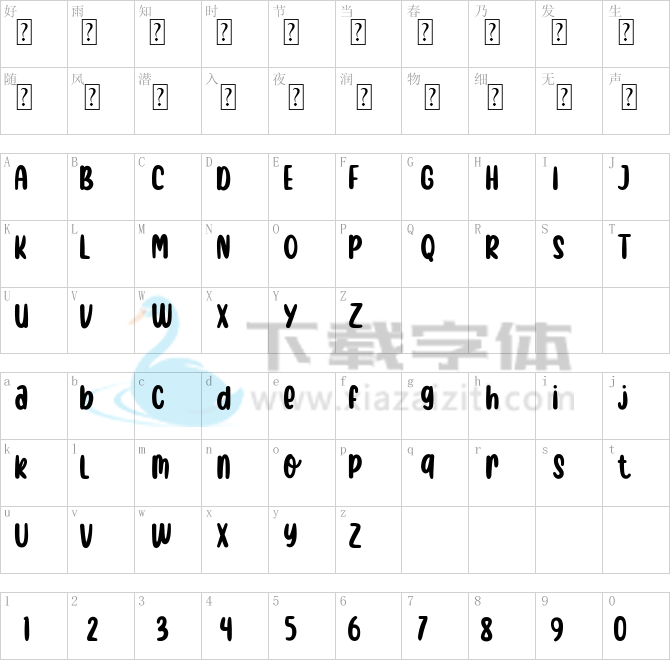
Alexander Display.ttf字体下载,这款字体结构工整、笔画清晰,兼顾美观与易读性,适用于标题、正文、海报、包装、LOGO 等多种场景。字形优雅稳定,风格百搭耐看,适配日常排版与创意设计,让文字呈现更舒适、更具质感。Alexander Display.ttf字体下载一笔一画,皆是细节,以均衡的比例、流畅的线条打造舒适视觉体验,字形端正大气,风格简约现代。无论是商业设计、品牌宣传还是日常排版,都能轻松驾驭,让文字更有格调与力量。Alexander Display.ttf字体下载字体下载。
Alexander Display.ttf图片展示
Alexander Display.ttf字体属性详情
• 字体名称:Alexander Display
Alexander Display.ttf映射图